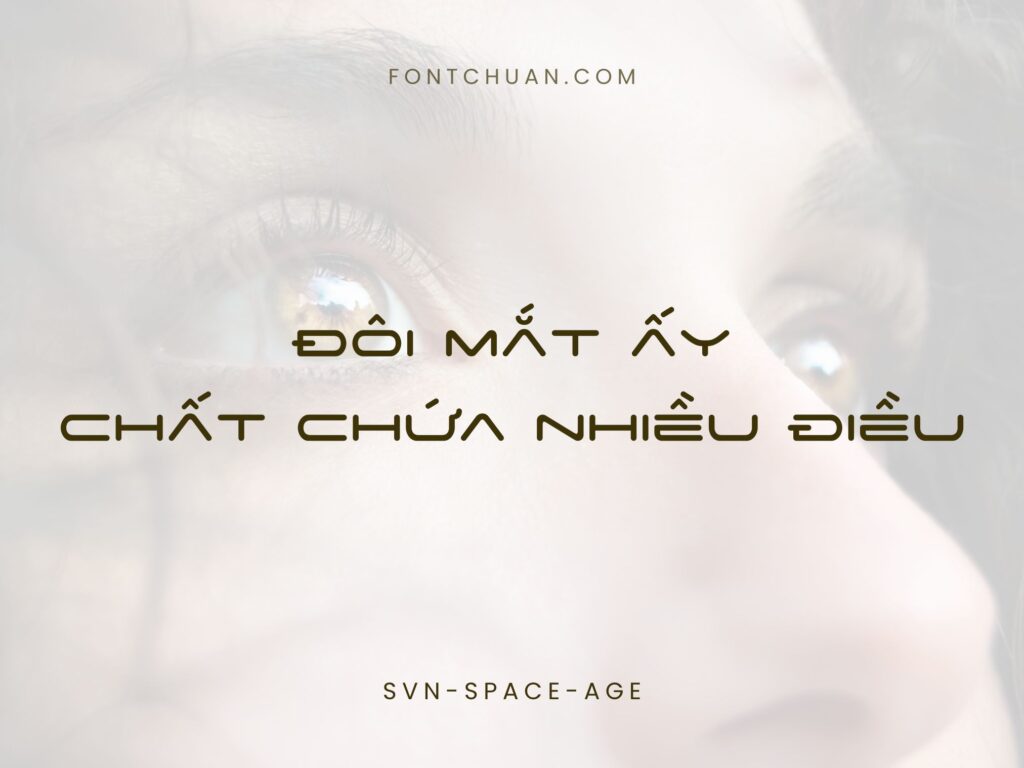
Font SVN Space Age là phiên bản Việt hóa của kiểu chữ Space Age, được thực hiện bởi STYLEno.1 Fonts. Space Age là một Font Decorative hiển thị mang phong cách khoa học viễn tưởng, được thiết kế bởi Justin Callaghan, lấy cảm hứng từ logo của khu vui chơi Epcot’s “Mission: SPACE”. Font này nổi bật với các ký tự in hoa đồng nhất về chiều cao, các nét chữ góc cạnh và hiện đại, tạo nên sự mạnh mẽ và tương lai trong thiết kế. Space Age bao gồm đầy đủ các ký tự chữ hoa, chữ thường, chữ số và các ký tự đặc biệt, hỗ trợ đa ngôn ngữ, phù hợp cho nhiều mục đích sử dụng khác nhau như thiết kế logo, tiêu đề, bao bì sản phẩm và các ấn phẩm truyền thông.
SVN Space Age lý tưởng cho các dự án thiết kế yêu cầu sự hiện đại và tương lai, như thiết kế logo, tiêu đề, bao bì sản phẩm và các ấn phẩm truyền thông. Các ngành nghề như công nghệ, quảng cáo và giáo dục có thể tận dụng font này để tạo điểm nhấn trong thiết kế. Ngoài ra, font cũng thích hợp cho các sự kiện như Tết, Giáng sinh, Halloween và các lễ hội khác.